Ein Digital-Lettering-Kurs lohnt sich durchaus, selbst wenn die Hand nach Jahren mit Brush-Pen und Papier längst weiß, was sie tut. Diese Frage stelle ich mir jedes Mal aufs Neue, wenn eine weitere App mit vollmundigen Versprechen für Tablet-Handlettering im Store auftaucht. Kreativ-Apps verkaufen sich über hübsche Pinsel-Presets, aber ein Kurs für alle, die Procreate lernen wollen, muss mehr liefern als eine Bedienungsanleitung für Werkzeugleisten. Bevor ich irgendeine App empfehle, prüfe ich deshalb, ob der dazugehörige Kurs Buchstaben lehrt oder nur Software.
Der Glasbildschirm kennt keinen Papierwiderstand
Der Umstieg von Papier auf Glas bringt eine Sache brutal ans Licht: Jede Gewohnheit, die sich über Jahre auf Clairefontaine-Papier eingeschliffen hat, funktioniert auf einer glatten Tablet-Oberfläche nicht automatisch weiter. Es fehlt der Widerstand, gegen den die Hand normalerweise arbeitet, und genau dieser Unterschied wird in den meisten Kursbeschreibungen mit keinem Wort erwähnt. Wer nur die Menüs einer App erklärt bekommt, merkt das oft erst, wenn der erste Schwung auf dem Bildschirm eckig statt weich ausfällt.
An meinem runden Küchentisch in der Altbauwohnung in Bonn-Beuel steht inzwischen neben den Tuschefläschchen auch das Tablet, und abends fällt das kühle Licht der Klemmleuchte nicht mehr nur auf einen Tintenklecks, der noch nicht ganz getrocknet ist, sondern ebenso auf das glatte Display daneben. Der Kontrast zwischen beiden Oberflächen erklärt mehr über digitales Lettering als jede Software-Beschreibung.
Wie viel von dem, was ein Kurs lehrt, den Wechsel zwischen zwei Apps eigentlich übersteht, beschäftigt mich, seit ich mehrere Programme parallel ausprobiert habe. Die Werkzeuglogik ähnelt sich zwischen den Apps oft verblüffend, die konkrete Bedienung dagegen kaum – ein Punkt, den ich in meinem Überblick zu Digital Lettering lernen ohne Vorkenntnisse ausführlicher aufgedröselt habe.
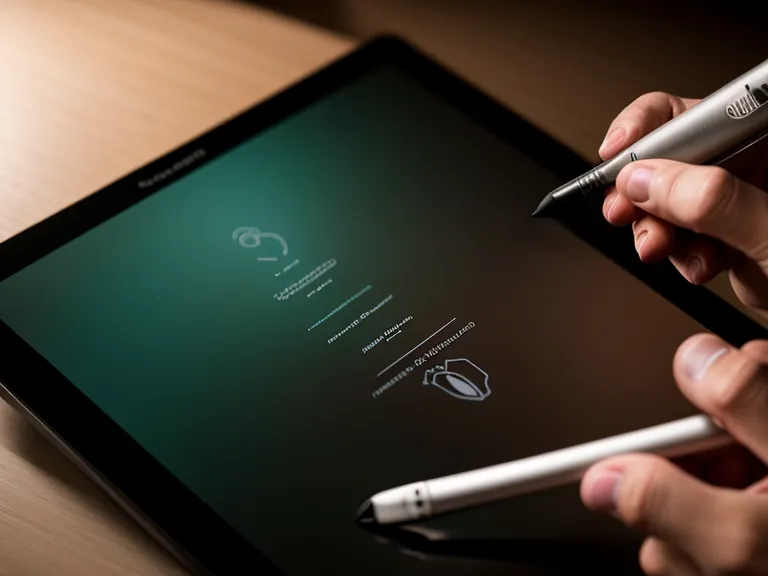
Procreate oder Illustrator: Pixel gegen Vektor
Fast jeder, der mit dem Tablet lettert, landet zuerst bei Procreate, und das aus gutem Grund: Die Pinsel-Engine fühlt sich organisch an, und Einsteiger kommen schnell zu ansehnlichen Ergebnissen. Als Grafikerin, die tagsüber in einer Bonner Agentur mit Druckvorlagen arbeitet, stoße ich bei der Technik dahinter trotzdem regelmäßig an eine Grenze: Procreate rechnet in Pixeln, und sobald ein Lettering großformatig gedruckt werden soll, zeigt sich das an ausgefransten Kanten.
Illustrator auf dem iPad verfolgt einen anderen Ansatz und arbeitet mit Vektorgrafik – jeder Strich bleibt eine mathematische Kurve, die sich auch Tage später noch punktgenau nachjustieren lässt, ohne dass die Kante darunter leidet. Wer die Anatomie eines Buchstabens einmal analog verstanden hat, erkennt sie im Vektor-Modus zwar wieder, muss sie dort aber neu übersetzen, weil jede Kurve einzeln sitzt statt sich unter einer Textur zu verstecken. Genau das zwingt dazu, sauber zu konstruieren statt nur hübsch zu kolorieren.
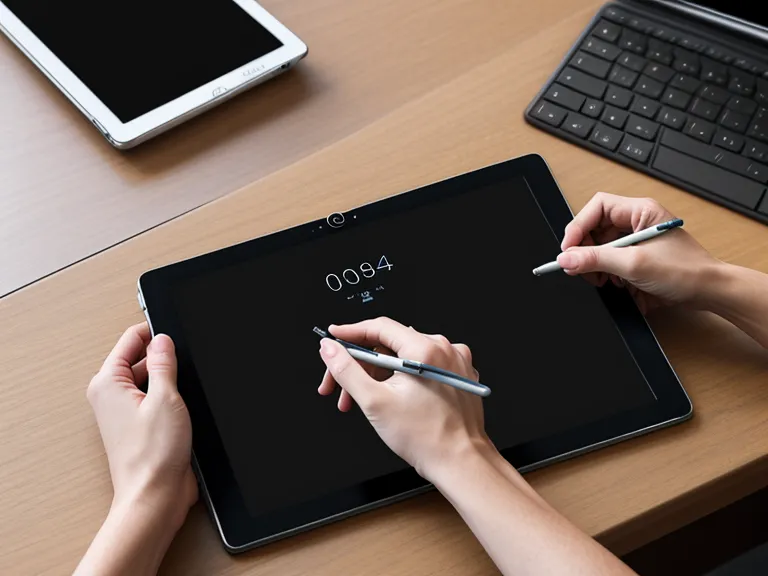
Kalibrieren, Exportieren, Drucken: Die technischen Nebenschauplätze
Bevor ein Kurs überhaupt zur Gestaltung kommt, sollte er kurz die Druckkurve ansprechen, also wie viel Kraft eine App braucht, bis ein Abstrich wirklich dick wird – mehr Tiefe zu diesem einen Thema gehört in einen eigenen, spezialisierten Kurs, hier reicht ein kurzer Hinweis. Ich erinnere mich noch gut an einen Abend, an dem ein Aufwärtsstrich plötzlich so leicht über den Bildschirm lief, dass ich kurz nachgesehen habe, ob ich aus Versehen die falsche Stiftspitze in der App aktiviert hatte.
Nebenbei bringt das glatte Display eine Belastung mit, die auf Papier seltener auftritt: Das Handgelenk verkrampft schneller, wenn man unbewusst versucht, den fehlenden Widerstand mit mehr Druck auszugleichen, und eine kurze Haltungskorrektur am Tisch hilft hier oft mehr als jede Software-Einstellung.
Genauso wichtig und in kaum einem Kurs Thema ist der Farbraum beim Export. Die meisten Apps arbeiten standardmäßig in sRGB, was auf dem Tablet-Display kräftig und satt wirkt, beim Druck auf Papier aber öfter stumpfer ausfällt, als man erwartet. Ein Kurs, der digitale Werke auch für den Druck vorbereiten will, sollte diesen Schritt nicht dem Zufall überlassen.
Woran sich ein guter Kurs erkennt
Meine Nachbarin Elisabeth Rudert fragt mich regelmäßig im Treppenhaus nach Anfänger-Kursen mit einem ordentlichen PDF-Begleitheft, weil sie lieber auf Papier nachliest, was sie gerade auf dem Bildschirm ausprobiert hat. Diese Kombination ist ein gutes Kriterium in der Praxis: Ein Kurs, der digitale Übungen mit greifbarem Begleitmaterial verknüpft, zwingt einen dazu, das Gelernte zweimal zu verarbeiten statt nur einmal durchzuklicken.
Christine Albers aus unserem Kreativ-Stammtisch würde an dieser Stelle vermutlich nur skeptisch die Augenbrauen heben, denn für sie ersetzt kein Tablet-Kurs die analoge Übungsphase, in der die Hand erst lernt, was sie später am Bildschirm nur noch abruft. Wie viel von dieser analogen Vorarbeit wirklich in die digitale Praxis hinüberträgt, wäre ein eigenes Thema für sich – ganz unrecht hat sie mit ihrer Skepsis jedenfalls nicht.
Die richtige App für euer Ziel
Bevor ich mich für einen strukturierteren Weg entschieden habe, hatte ich kurz eine App mit täglichen Übungs-Challenges installiert, die nach etwa zehn Tagen kommentarlos in der hintersten Ecke meines Homescreens verschwand. Tägliche Erinnerungen ersetzen offenbar keinen Plan, der erklärt, warum eine Übung überhaupt Sinn ergibt.
Wer vor allem für Logos oder Druckprodukte lettert, ist mit einem vektorbasierten Kurs auf lange Sicht besser bedient, auch wenn die Einstiegshürde etwas höher liegt als bei Procreate. Wer dagegen schnelle, organische Ergebnisse für Social Media oder private Karten sucht, kommt mit einem guten Procreate-Kurs vermutlich schneller zum gewünschten Gefühl. Für alle, die das Tablet ohnehin für andere Zwecke nutzen, habe ich kürzlich auch Sketchnotes lernen auf dem iPad unter die Lupe genommen, allerdings mit einem ganz anderen Anspruch an Tempo und Struktur.
Entscheidend bleibt am Schluss weniger die App als die Frage, ob ein Kurs die Systematik hinter den Buchstaben mitliefert oder nur eine hübsche Oberfläche. Meine Küchentischdecke jedenfalls bekommt inzwischen deutlich weniger neue Flecken ab, seit ein Teil der Übungsstunden auf dem Tablet stattfindet – der Rest der Familie honoriert das mit stillschweigender Erleichterung.